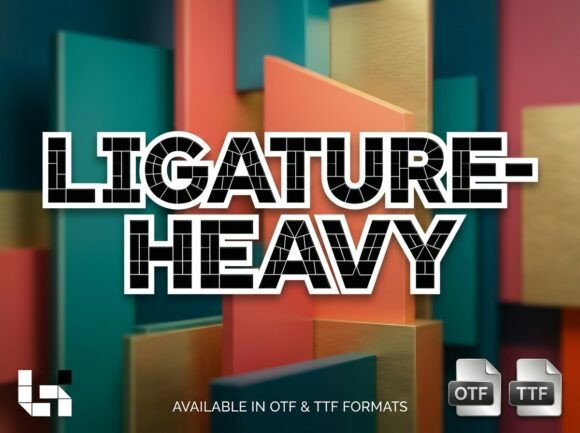
Ligature-heavy
Ligature‑Heavy: A Fonte que Transforma Estruturas Visuais em Impacto Brutalista
Se você procura uma tipografia que combine autoridade estrutural e intrincada geometria, Ligature‑Heavy é a escolha definitiva. Projetada para marcas que precisam de voz “concreta” e presença massiva, esta fonte display entrega o peso visual que arquitetos, designers de embalagens industriais e galerias de arte contemporânea exigem.
• Identidade de marca arquitetônica – Ideal para escritórios de arquitetura progressista que desejam comunicar solidez e inovação.
• Embalagens de hardware industrial – A espessura das linhas garante legibilidade mesmo em superfícies metálicas e ambientes de alta tecnologia.
• Banners de galerias de arte moderna – A geometria ousada complementa obras contemporâneas, criando um diálogo visual entre tipografia e exposição.
• Logotipos de startups de tecnologia – Transmite força e futurismo, perfeito para empresas que desejam se destacar no mercado digital.
• Títulos de jogos indie de quebra‑cabeça – A presença marcante da fonte atrai jogadores e acrescenta personalidade ao design do jogo.
• Headlines de marketing digital – Garante atenção imediata em campanhas online, aumentando taxa de cliques e engajamento.
Com ligaduras pesadas que unem caracteres de forma única, Ligature‑Heavy cria um efeito visual semelhante a blocos de concreto — sólido, imponente e impossível de ser ignorado. Sua estrutura brutalista faz com que cada palavra pareça esculpida, ideal para projetos que exigem impacto visual massivo e coerência estética.
Por que escolher Ligature‑Heavy?
• Versatilidade extrema – funciona perfeitamente em impressos, sites responsivos e sinalização física.
• Legibilidade aprimorada – mesmo em tamanhos grandes, as formas geométricas mantêm clareza e força.
Em resumo, Ligature‑Heavy não é apenas uma fonte; é um elemento estrutural que eleva a comunicação visual a um novo patamar de robustez e estilo. Adote-a hoje e dê à sua marca a presença de concreto que ela merece.